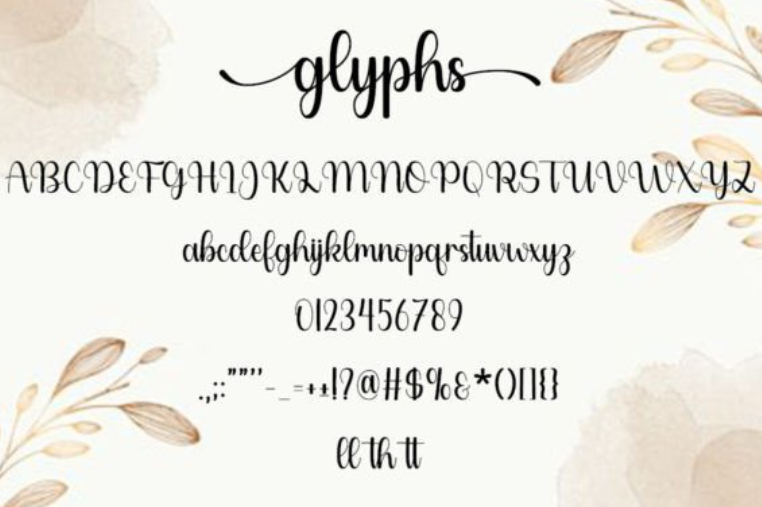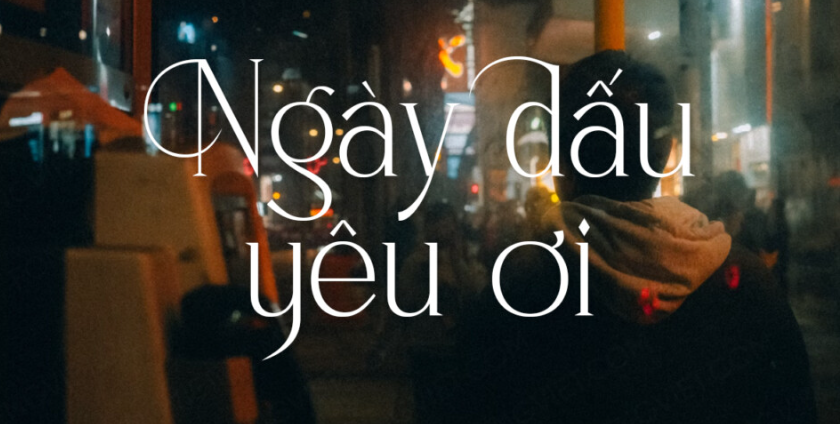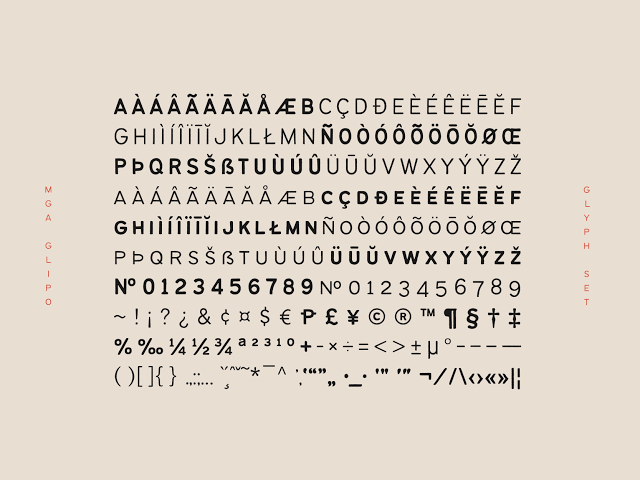
Font Glyphs Việt hóa là thuật ngữ chỉ các bộ phông chữ sở hữu bảng ký tự mở rộng (Glyphs panel) vô cùng phong phú, bao gồm hàng trăm ký tự thay thế (alternates), nét uốn lượn (swashes) và chữ ghép (ligatures) đã được tinh chỉnh hỗ trợ tiếng Việt hoàn chỉnh. Những phông chữ này là công cụ tối thượng giúp các designer biến hóa linh hoạt từng con chữ thành các tác phẩm Typography độc bản, không đụng hàng trên các thiết kế bao bì và bộ nhận diện thương hiệu cao cấp. Doozypack.vn cung cấp link tải trọn bộ Font Glyphs Việt hóa miễn phí chuẩn kỹ thuật, giúp bạn sở hữu kho ký tự ẩn đồ sộ này mà không lo gặp bất kỳ lỗi hiển thị dấu thanh nào khi thiết kế in ấn.
Bảng Glyphs trong font chữ là gì và tại sao designer cần font Glyphs Việt hóa?
Bảng Glyphs (OpenType Panel) là kho lưu trữ toàn bộ các ký tự ẩn, hình vẽ trang trí và các biến thể chữ cái mà tác giả thiết kế tích hợp bên trong một tệp phông chữ duy nhất.
Mẫu ký tự Glyphs độc đáo
Khám phá thế giới ký tự ẩn và nét uốn (Alternates & Swashes)
Đặc trưng lớn nhất của các bộ Font Glyphs hỗ trợ tiếng Việt chất lượng cao là ngoài bảng chữ cái tiêu chuẩn, chúng còn cung cấp hàng loạt lựa chọn thay thế cho từng chữ cái (ví dụ chữ ‘A’ hay ‘e’ có thể có từ 3 đến 5 kiểu dáng uốn lượn khác nhau). Khi sử dụng các dòng font này, designer có thể chủ động thay đổi hình dáng ký tự để tạo ra độ mở hài hòa cho bố cục, biến tên thương hiệu hoặc tiêu đề bao bì trở nên uyển chuyển, nghệ thuật và mang đậm dấu ấn cá nhân.
Giải quyết triệt để lỗi mất ký tự và dấu tiếng Việt
Nhiều phông chữ nước ngoài có bảng Glyphs rất đẹp nhưng khi gõ tiếng Việt lại bị mất dấu hoặc không thể mở khóa các ký tự trang trí vì thiếu bộ mã mở rộng. Các phiên bản Font Glyphs Việt hóa tại Doozypack.vn đã được tối ưu hóa toàn diện, bảo đảm rằng khi bạn kích hoạt các biến thể ký tự ẩn, hệ thống dấu thanh tiếng Việt vẫn đi kèm mượt mà và chuẩn xác tuyệt đối.
Ưu điểm nổi bật của các bộ font Glyphs hỗ trợ tiếng Việt
Khi ứng dụng các phông chữ có bảng ký tự mở rộng vào thiết kế thương mại, sự chuẩn xác về kỹ thuật in ấn là yếu tố tối quan trọng:
• Tự do tùy biến Typography: Giúp bạn dễ dàng tạo ra các logo độc bản, tiêu đề hộp quà tặng hoặc nhãn mác sản phẩm không bị trùng lặp với bất kỳ ai nhờ kho ký tự thay thế khổng lồ.
• Tương thích chuẩn bảng mã Unicode: Bản font cho phép bạn dễ dàng soạn thảo nội dung trên các bộ gõ tiếng Việt thông dụng như Unikey hay EVKey, hiển thị mượt mà trên mọi phần mềm đồ họa hiện đại.
• Bảo đảm tính đồng nhất thương hiệu: Việc sử dụng bản font chuẩn giúp bạn tự tin dàn trang tiêu đề tiếng Việt mà không lo hiện tượng lỗi ô vuông hay nhảy về font hệ thống khô khan.
Thiết kế typography sáng tạo
Ứng dụng thực tế của font nhiều Glyphs trong sản xuất bao bì tại Doozypack.vn
Sự linh hoạt của các bộ font Glyphs mang lại hiệu ứng thị giác đắt giá trên các dòng sản phẩm bao bì thực tế do Doozypack.vn sản xuất:
• Hộp giấy đựng Nước hoa & Mỹ phẩm Luxury: Tiêu đề thương hiệu in bằng phông chữ Script nhiều Glyphs kết hợp kỹ thuật ép kim mờ (Matte Gold) trên nền hộp đen nhám tạo nên vẻ đẹp sang trọng chuẩn phong cách thời trang cao cấp.
• Thiệp cưới & Hộp quà tặng doanh nhân: Các ký tự uốn lượn (swashes) được tinh chỉnh từ bảng Glyphs giúp nắp hộp quà toát lên vẻ trang trọng, lịch lãm và đầy tính trân trọng đối với người nhận.
• Nhãn dán chai Rượu vang & Nến thơm: Tên dòng sản phẩm in bằng font chữ nhiều ký tự thay thế giúp nhãn dán toát lên vẻ cổ điển, nghệ thuật và khẳng định phẩm cấp thượng hạng.
Ký tự nghệ thuật trên ấn phẩm